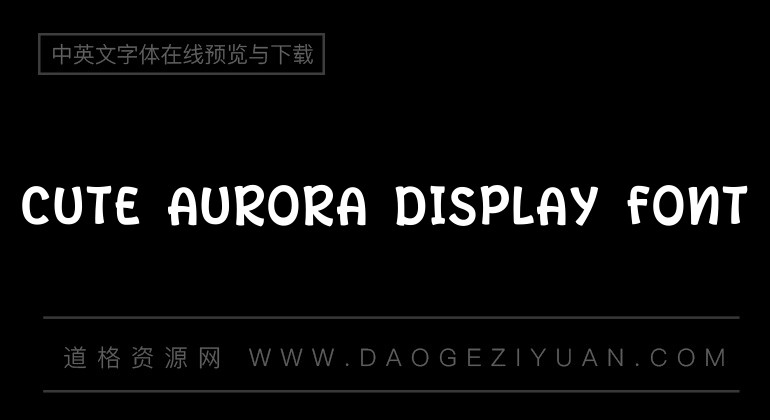
Cute Aurora Display Font 是一种可爱的字体,适用于各种设计项目,包括海报、名片、标志、包装和其他品牌物料。它的设计风格感觉像是从光亮的极光和星空中汲取灵感,所以它的字形通常是流畅的、优美的和时尚的。 这种字体的特点是字母非常清晰,易于阅读,而且非常适合用于标题和其他突出显示的文本。它有多个变体,包括粗体和斜体,可以根据需要选择不同的字重。此外,这种字体还可以在不同的大小和颜色下使用,以适应各种设计需求。 总的来说,Cute Aurora Display Font 是一种非常流行的字体,特别适合风格轻松、可爱和时尚的项目。无论是在印刷品还是数字媒体上,它都是一个很好的选择。内容介绍
Cute Aurora Display Font是一款非常不错的手写艺术字体,具有很好的视觉感,适合于文化类的宣传设计、商业类品牌的广告和产品包装设计以及个性化文字排版等较多场景。